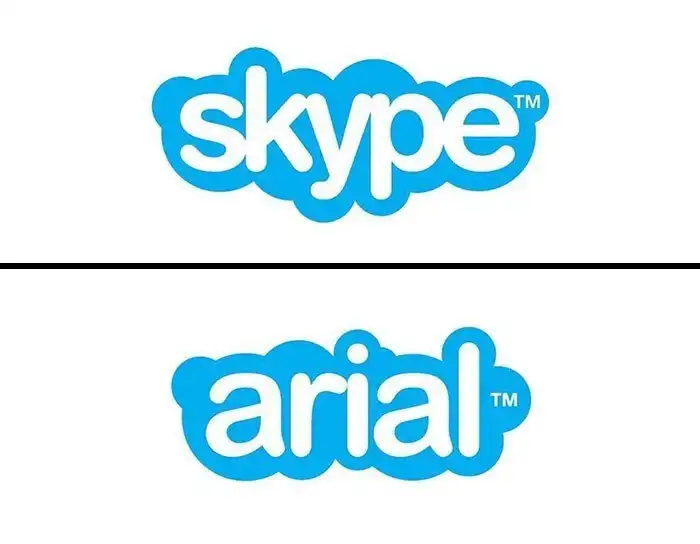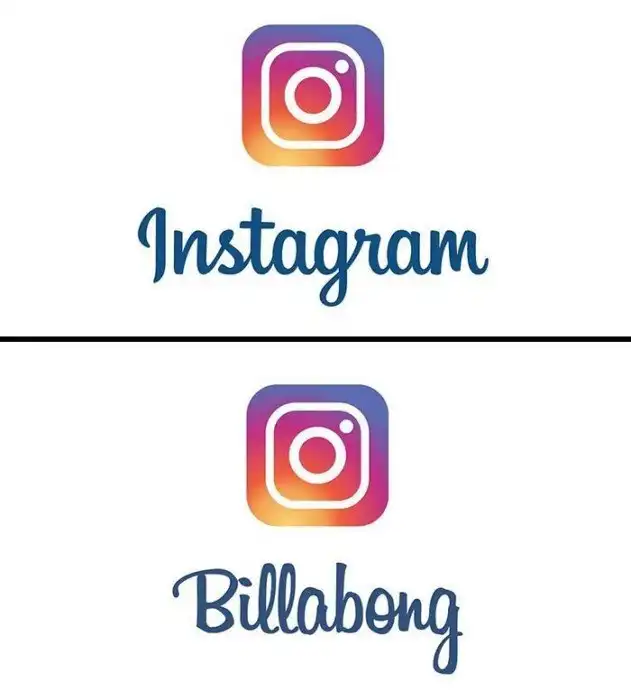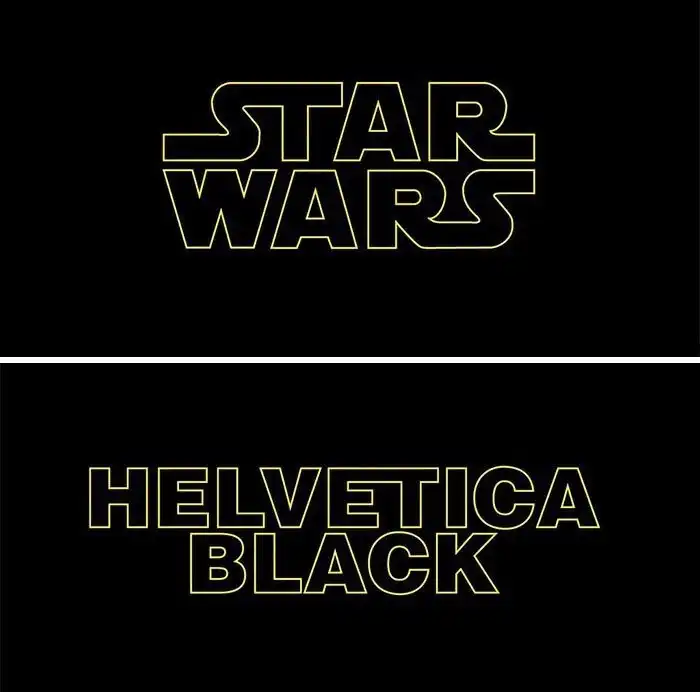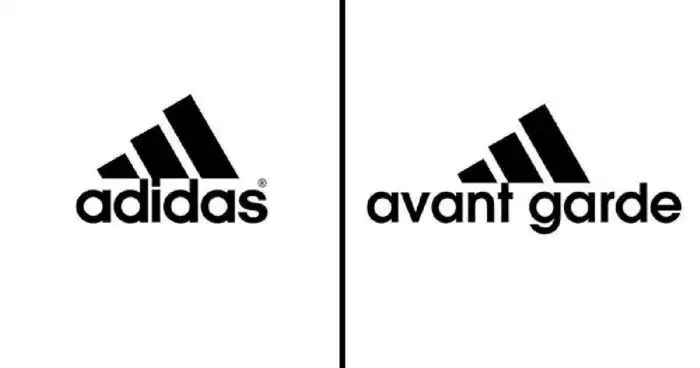
Некоторые бренды используют хорошо известные и проверенные временем шрифты, такие как Helvetica, Arial и Gotham, а другие создают собственные. Итальянский графический дизайнер и гуру логотипов Эмануэле Абрате ведет аккаунт в Instagram, посвященный этой теме.
По словам Эмануэле, идея проекта под названием "Логошрифты" появилась спонтанно. Начинающие графические дизайнеры, обращавшиеся к нему за советом, часто задавали одни и те же вопросы. Одним из них был вопрос "Какой шрифт тут использован?".
"Поэтому я решил создать проект, который отвечал бы на этот вопрос быстро и наглядно", - объяснил художник.
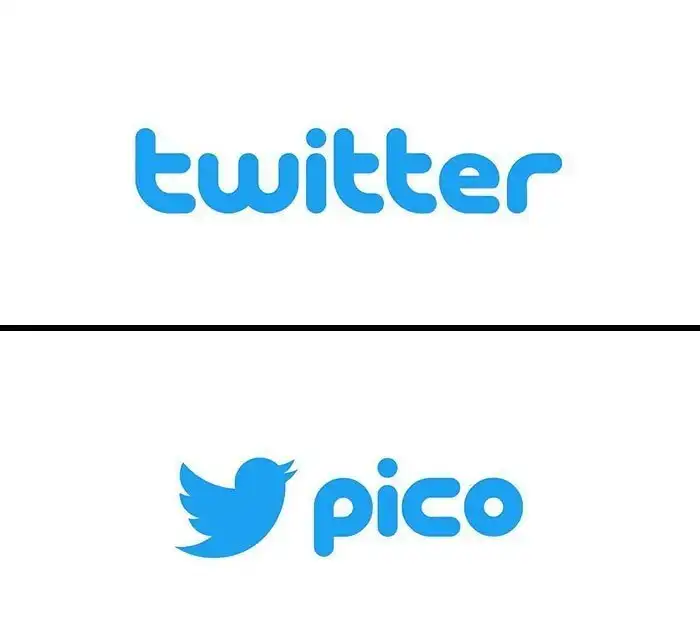
"Самые известные логотипы используют нестандартную типографику (разработанную с нуля или на основе уже существующего шрифта с последующей кастомизацией). Моя цель - выяснить, какой шрифт используется вначале, а затем изменить его, чтобы получить окончательный результат. Для этого я провожу поиск, просматривая руководства по брендам, а затем визуально сравнивая исходный шрифт с логотипом. Я также часто использую такие инструменты, как "whatthefont". Я всегда стараюсь быть максимально точным", - рассказал Эмануэле.
Основная цель проекта Logofonts, у которого уже 45,1 тыс. подписчиков в Instagram, - показать, как важен выбор шрифта при разработке логотипа. Просто по той причине, что он может вызывать у людей эмоциональный отклик, связанный с тем, что они уже видели что-то похожее на другом известном логотипе...
Представьте, что кто-то использует в своем логотипе типографику, например, Coca-Cola. Ну и кому нужны неизбежные ассоциации с производителем газировки? Конечно же, нужно подобрать шрифт так, чтобы логотип выглядел уникальным и не похожим на уже существующие.